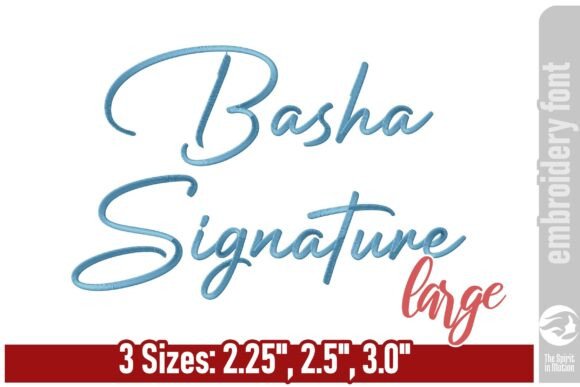
Basha Signature Font - Large
Die richtigen Designelemente zu finden, kann eine Herausforderung sein, aber Basha Signature Font - Large bietet eine außergewöhnliche Sammlung, die Ihre Arbeit sofort aufwertet.
Egal, ob Sie POD-Produkte (Print on Demand), Hochzeitseinladungen oder Social-Media-Grafiken erstellen, Basha Signature Font - Large ist die ideale Wahl.